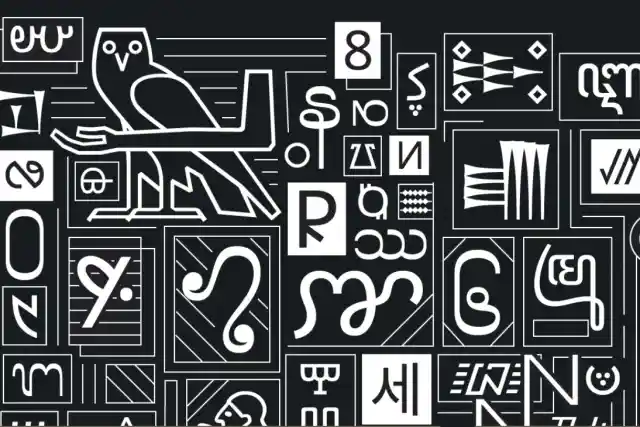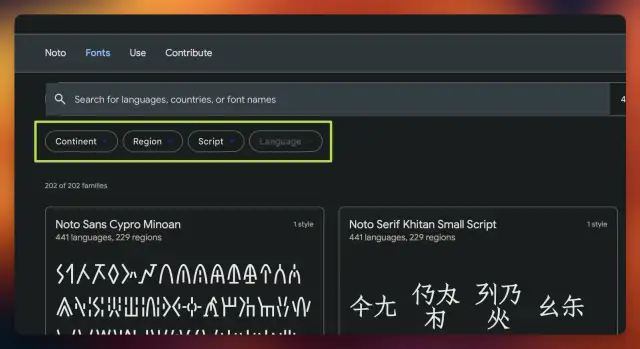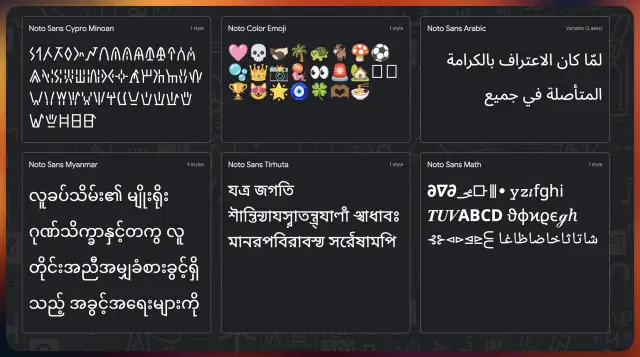
Google Fonts und die Noto
Es gibt Schriften für Asien, Ost- und Zentraleuropa oder Afrika. Und dann gibt es die kostenlose Noto von Google: ein Font der Extreme.
Fonts können ziemlich abstrakt ausfallen
Google Fonts ist heute mit Fug und Recht eine der ersten Anlaufstellen für Schriften. Unter fonts.google.com finden Sie eine riesige und grösstenteils hochwertige Auswahl – und keinen Ramsch wie bei «50’000 Schriften für jeden Zweck»-Angeboten. Zudem sind sämtliche Fonts kostenlos und dürfen auch für kommerzielle Zwecke verwendet werden.
Einer dieser Fonts nimmt jedoch eine besondere Stellung ein: die Noto, die Sie unter fonts.google.com/noto finden. Der Name ist eine Verballhornung von «NO more TOfu» – nie mehr Tofu. Mit «Tofu» sind die Kästchen gemeint, die in einem Text erscheinen, wenn eine Schrift ein Zeichen nicht wiedergeben kann. Und damit ist der Zweck der Noto klar: Sie möchte jedes existierende Zeichen abbilden.
Nur eine kleine Auswahl der Schriftsysteme, die die Noto abdeckt
Neben den diakritischen Zeichen unterstützt die Noto auch Griechisch, Kyrillisch, Brüche sowie zahlreiche Sonderzeichen. Kurz, sie deckt den gesamten (ost-)europäischen Raum inklusive Russland und Griechenland ab – und das alles kostenlos.
Sie finden die Noto aber auch für unzählige weitere Schriftsystemen – darunter Mongolisch, Sinhala, Lao und noch ein paar andere, die die meisten von uns nicht einmal aussprechen können. Oft sind es nur ein oder zwei Schnitte, doch in vielen Schriftsystemen gibt es ohnehin keine Auszeichnungen wie fett oder kursiv. Diverse Schriften sind ausserdem als serifenbetonte und serifenlose Variante vorhanden.
Wenn Sie einen Font anklicken, lässt sich ein individuelles Schriftmuster herstellen. Dazu müssen Sie allerdings der jeweiligen Sprache (und ihrer Tastatur) mächtig sein. Wenn Sie wissen möchten, wie Ihr Name in der Noto Sans Cypro Minoan aussieht, werden Sie nach der Eingabe nur lateinische Zeichen sehen – denn jedem Buchstaben liegt ein streng definierter Unicode zugrunde. So ist der lateinische Buchstabe «D» unter Unicode U+0044 zu finden, das griechische «Δ» (Delta) hingegen unter Unicode U+0394. Wenn Sie Ihren Text also in lateinischen Buchstaben eingeben, werden Sie nie etwas anderes sehen als lateinische Schriftzeichen.
Noch ein letztes Wort zur «Noto Sans Cypro Minoan»: Die kypro-minoische Silbenschrift ist gemäss der englischen Wikipedia eine nicht entzifferte Silbenschrift, die auf der Insel Zypern während der späten Bronzezeit (ca. 1550-1050 v. Chr.) verwendet wurde.
Gut zu wissen … dass Google bei der Noto keine halben Sachen macht.